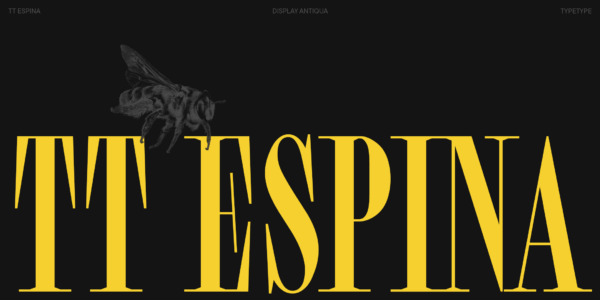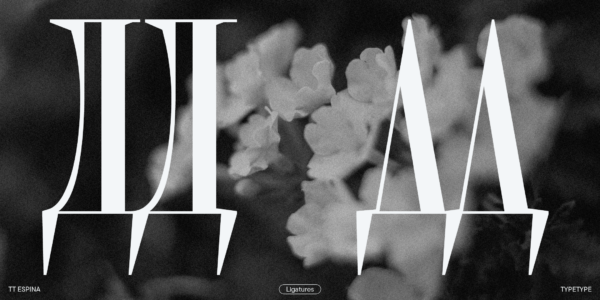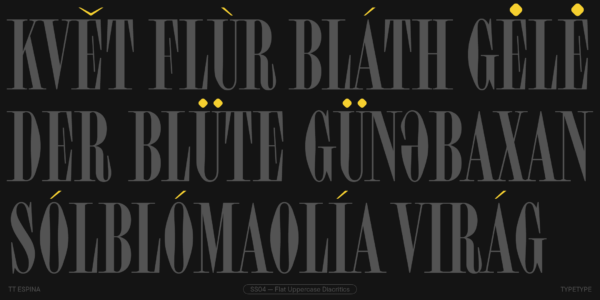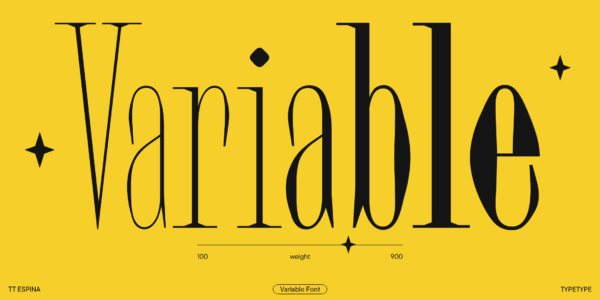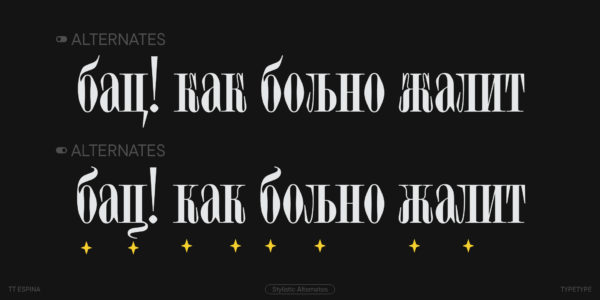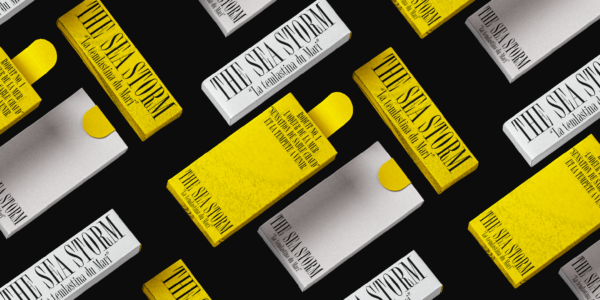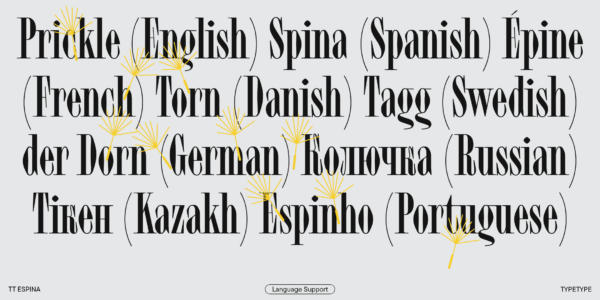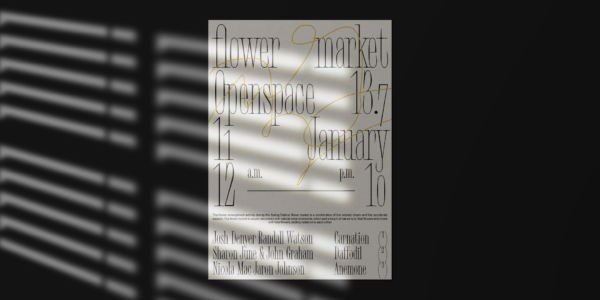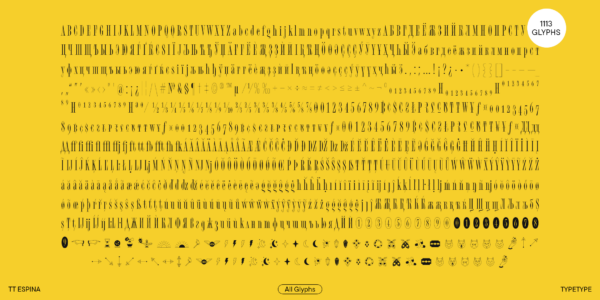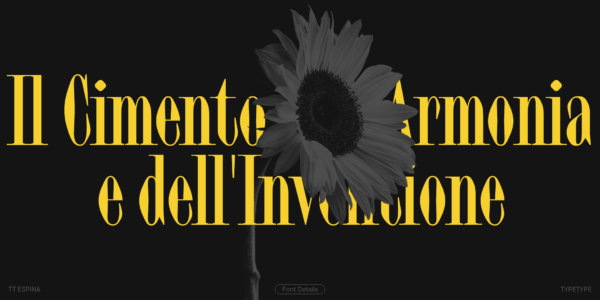
TT Espina
TT Espina — ТТ Эспина
Произносится «ТТ Эспина». «Espina» в переводе с английского «колючка». Буквы «TT» являются аббревиатурой названия компании.
TT Espina — дисплейная антиква с выразительными засечками. Узкие пропорции и ромбовидные окружности придают этому шрифту особую эстетику.
TT Espina — акцидентная антиква с выразительными засечками
Шрифтовая гарнитура TT Espina выделяется среди других антикв благодаря высокому контрасту, крупным выразительным засечкам, закрытой апертуре и ромбовидным окружностям. Знаки в шрифте довольно узкие, что придает особую эстетику макетам, в которых он используется. Каждую букву в TT Espina хочется внимательно разглядывать, поэтому заголовки, набранные этим шрифтом, обязательно привлекут внимание. А комплект иконок, входящий в гарнитуру — это приятное дополнение для дизайнеров, которые будут работать с нашим шрифтом-бриллиантом.
Семейство состоит из 7 начертаний: 6 прямых и 1 вариативного
TT Espina чувствует себя особенно комфортно на билбордах и витринах магазинов
Улучшили акцидентный шрифт TT Espina и добавили поддержку кириллицы!
В версии 2.000 — полностью обновленный кернинг, усовершенствованный хинтинг, еще больше OpenType фич, расширенный кассовый состав и новые стилистические сеты.
TT Espina — дисплейная антиква с выразительными засечками. При ее создании дизайнеры вдохновлялись исторической формой буквы «O», которая приобретала ромбовидную форму из-за качества печати. В результате получилась актуальная шрифтовая гарнитура с высоким контрастом между горизонталями и вертикалями.
TT Espina служит очередным доказательством того, что антиква может стать стильным и выразительным акцидентным шрифтом, подходящим для современных проектов. Он будет гармонично смотреться в заголовках постеров или афиш, в оформлении галерей и выставок, в крупноформатной печатной продукции или на сайтах.
От других антикв этот шрифт легко отличить, в первую очередь, по узким пропорциям, а также высокому контрасту, выразительным и крупным засечкам, закрытой апертуре и ромбовидным окружностям. Узкие знаки придают TT Espina особую эстетику. В каждую букву хочется всматриваться, так что заголовки, оформленные TT Espina, точно привлекут внимание. Приятное дополнение для дизайнеров — обширный сет различных иконок.
В обновленной версии мы улучшили и расширили кернинг, доработали и хинтинг для всех знаков, дорисовали расширенную кириллицу и дополнили латиницу, расширили основной и минускульный набор валют, добавили дроби, цифры для нумераторов и денумераторов, а также добавили новые стилистические сеты для кириллицы, нуля с точкой и закрашенных/незакрашенных нумераторов-шаров.
TT Espina версии 2.000 — это:
• 7 начертаний: 6 прямых и 1 вариативный шрифт;
• 1113 глифов в каждом начертании;
• 38 OpenType фич, в том числе возможность менять формы некоторых символов, а также заменять знаки с высоко посаженной диакритикой на знаки с низко посаженной диакритикой, что удобно для оформления плакатов с плотным интерлиньяжем;
• Поддержка более 230 языков.
Дата выхода и обновления
Публикация: 2 августа 2022
Обновление: 6 февраля 2024
Что изменилось в шрифте:
• Увеличился кассовый состав: количество знаков выросло с 648 до 1113;
• Добавились новые OpenType фичи: их количество выросло с 21 до 38;
• Появилась поддержка кириллицы;
• Выросло количество поддерживаемых языков: теперь в шрифте их 230;
• Полностью обновился кернинг — мы улучшили и расширили его;
• Обновился хинтинг для всех знаков — его мы доработали и усовершенствовали;
• Дополнились расширенные кириллица и латиница;
• Расширился набор валют — основной и минускульный, появились дроби, цифры для нумераторов и денумераторов;
• Добавились новые стилистические сеты для кириллицы, нуля с точкой и закрашенных/ незакрашенных нумераторов-шаров.